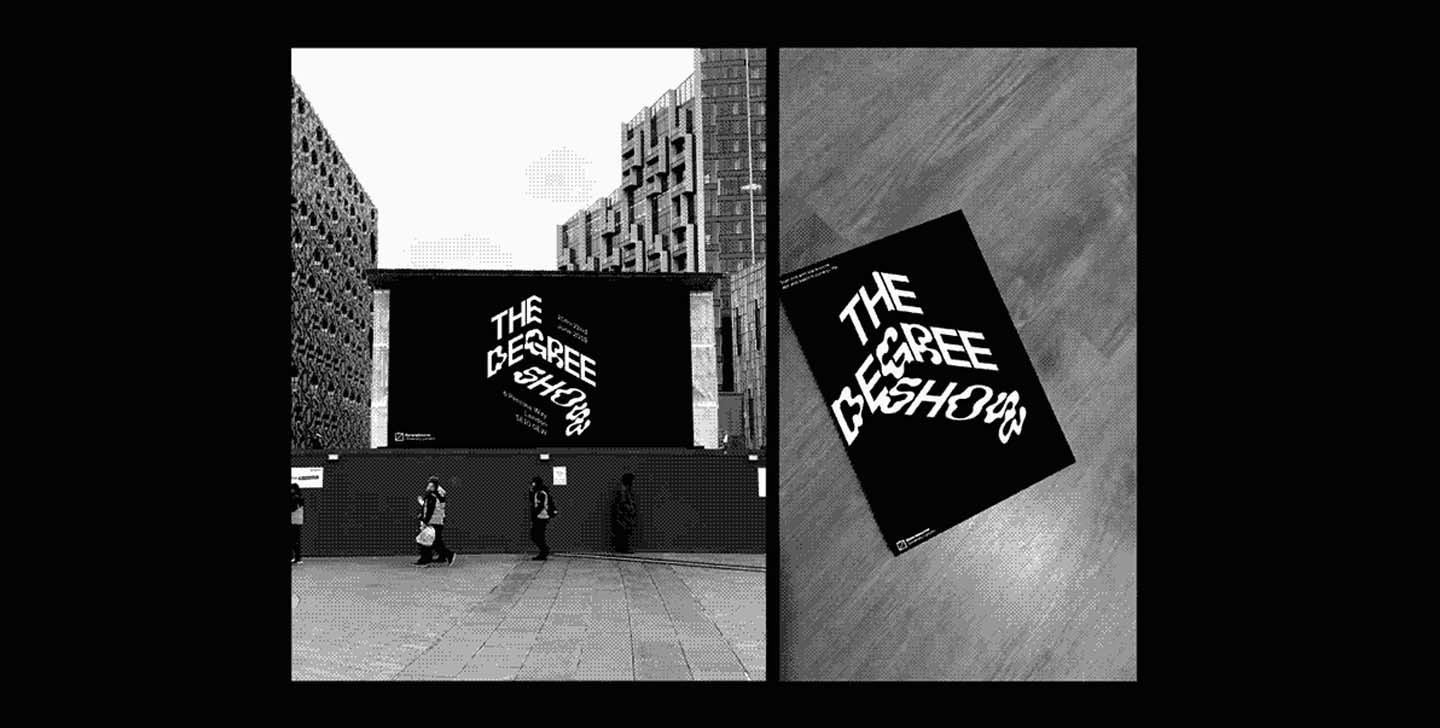
Por esa misma razón, no es casualidad que una tipografía caótica y ecléctica esté acaparando gran parte de la atención en el presente. ¿Qué puede ser más apropiado para los tiempos que corren, verdad? Si algo nos ha dejado claro el 2020 es que nos encontramos en una época voluble, de cambio constante y así lo reflejan las tipografías que más estamos viendo últimamente.
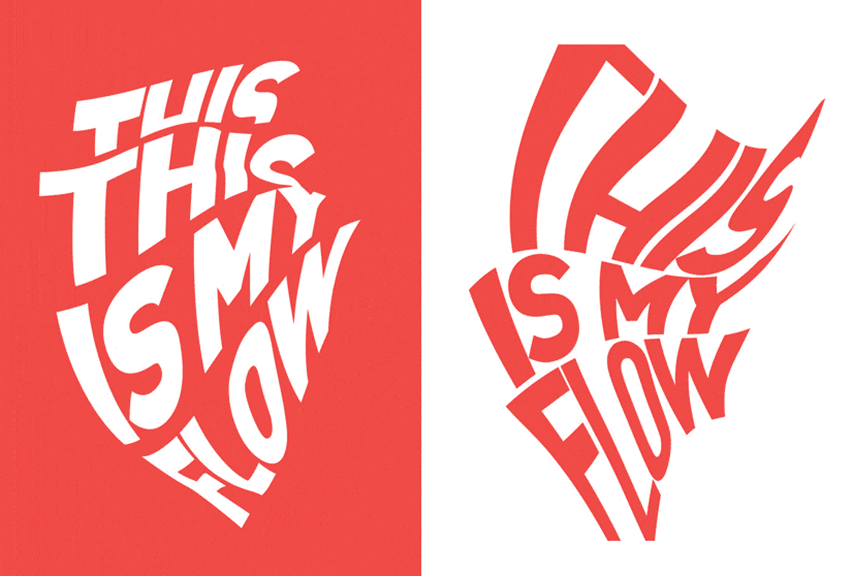
¿Qué letra define este año?
Falta de alineación de texto, mezcla en el orden de tipos, distorsión en las formas… Parece ser que el 2021 va a ser un año igual de diverso para las tendencias en fuentes y su versatilidad, con la peculiaridad y originalidad como características principales. Las tipografías cinéticas y las fuentes distorsionadas o experimentales (como la realizada por Tommi Shapr ¡a partir de patatas! No te pierdas el proceso) son tendencias emergentes que seguiremos viendo.
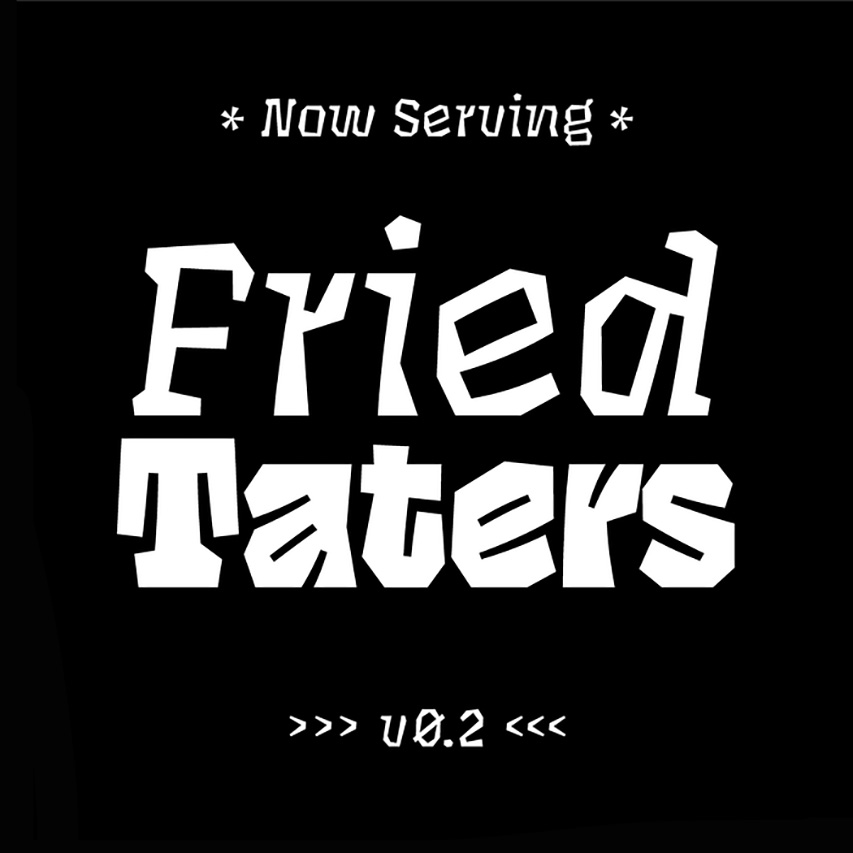
La tipografía cinética o Kinetic Typography ha experimentado una evolución increíble en los últimos años. Se define como el arte de crear tipografía en movimiento con el fin de transmitir un concepto a través de la animación de texto. Sus medios habituales son: los créditos de largometrajes, spots publicitarios de TV, videos musicales o comerciales, producciones de animación, y un largo etc. Cada vez más presente y más en acción, más integrada en su entorno.
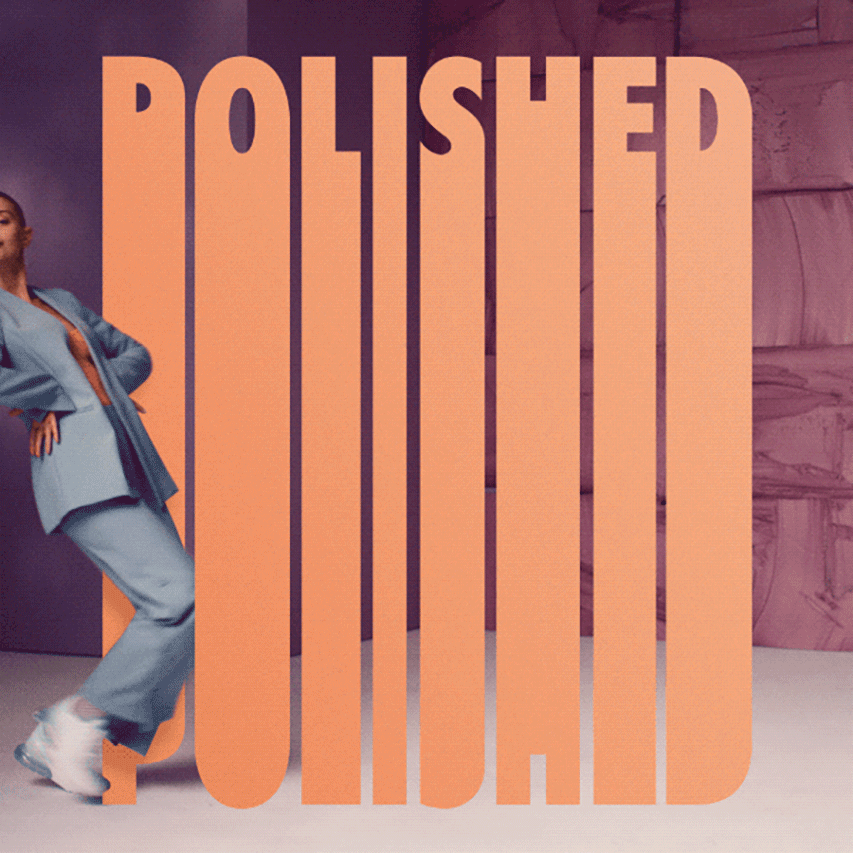
Sin embargo, gran parte de su éxito actual es debido a que muchas marcas han desarrollado su identidad visual en función de un sistema cinético, flexible y adaptativo, tomando el movimiento como protagonista corporativo. Los logos ya no se ven sólo en dos dimensiones, sino que las identidades visuales están en movimiento, son cambiantes y tridimensionales, dando lugar a fuentes distorsionadas que las hacen únicas.
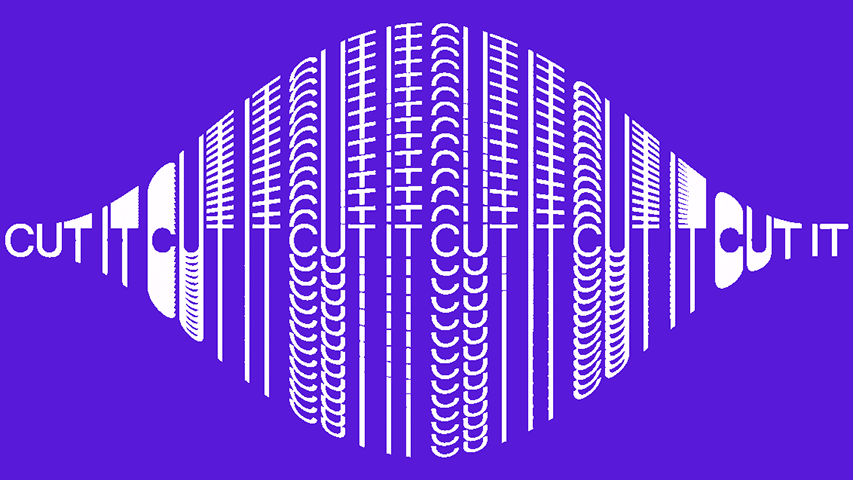
Tipografía en tres dimensiones
¿Y si a todo esto le añadimos una pizca del próximo artículo (a punto de salir del horno) sobre la Realidad Aumentada? Pues el resultado sería Weird Type, una app que te permite interactuar con tipografía 3D en el espacio.
El creativo Zach Lieberman, en colaboración con Design Indaba y Molmol Kuo, es el responsable de este nuevo concepto de aplicación móvil. Además, la app permite superponer imágenes, cambiar la forma o el tamaño de la tipografía, e incluso caminar físicamente a través de ella mientras la vamos creando.
Según palabras de su propio creador:
“El espacio es una variable importante para los diseñadores, especialmente a medida que avanzamos hacia sistemas AR y VR; sin embargo, estamos acostumbrados a diseñar tipos en cuadrículas 2D y cartesianas. En cambio, el espacio 3D y el movimiento ofrecen desafíos interesantes. Por eso, esta aplicación proporciona una interfaz intuitiva para jugar con la tipo en el espacio.”
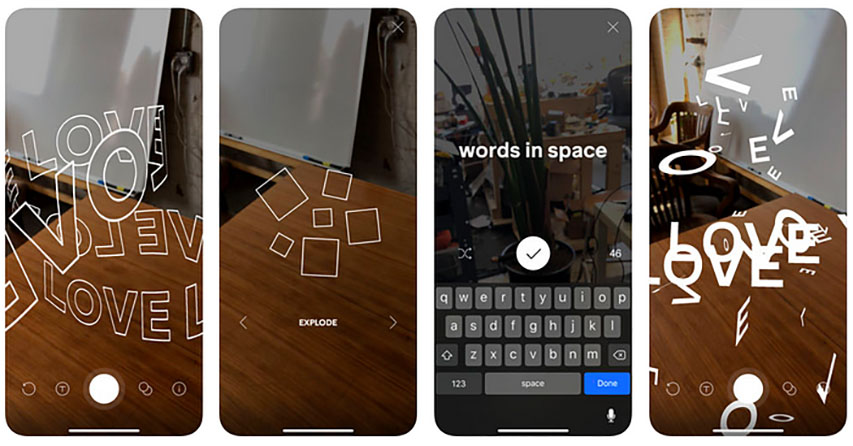
Otro buen ejemplo de llevar la tipografía en movimiento a otra dimensión es esta campaña en Realidad Aumentada realizada por la agencia de diseño londinense OMSE. La identidad gráfica se basa en las antiguas imprentas europeas donde la tipografía se distorsiona para asemejar los cilindros usados en las prensas tradicionales de las impresoras.
Lo interesante es que el usuario puede moverse alrededor y experimentar la campaña en un espacio tridimensional proporcionando así una experiencia inmersiva.
Cuando las imágenes se ven a través de la app de la campaña usando la cámara del teléfono, ¡las figuras cilíndricas comienzan a rotar! Además del efecto wow, esta tecnología también se emplea para mostrar detalles adicionales de la campaña, como información sobre el evento o nombres de artistas.
Estamos en un momento único de transformación en la historia, con grandes cambios en nuestra sociedad, ¡por lo que la tipografía no será una excepción! Una evolución inconformista y visual que sigue dando forma a nuestros mensajes cada vez con más creatividad y dinamismo.